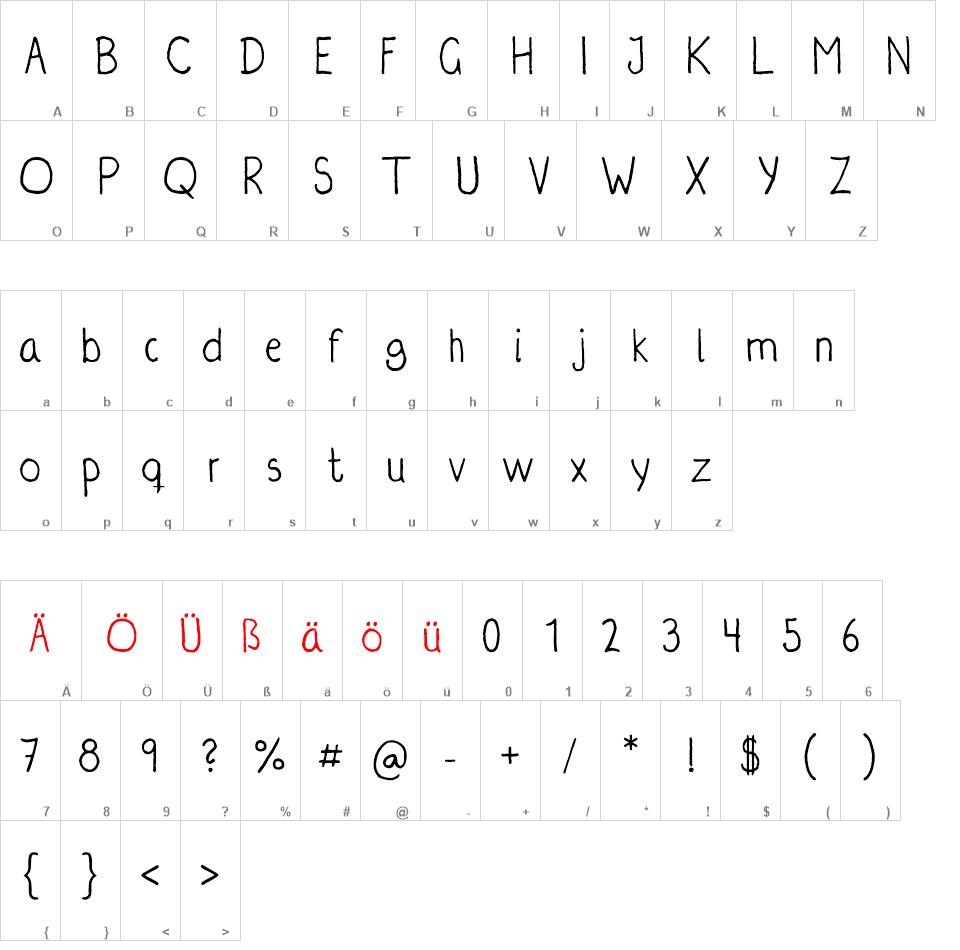
Irregularis
Irregularis font
Irregularis
Irregularis ist eine handschriftliche Schrift, die von Arman Ay entworfen wurde. Es zeichnet sich durch seinen lässig einfachen, aber unregelmäßigen handschriftlichen Stil aus und wurde sowohl für den persönlichen als auch für den kommerziellen Gebrauch geschaffen. Die Schrift wurde von zahlreichen Experten anerkannt, darunter Luc Devroye, Professor an der School of Computer Science der McGill University in Montreal, Kanada.